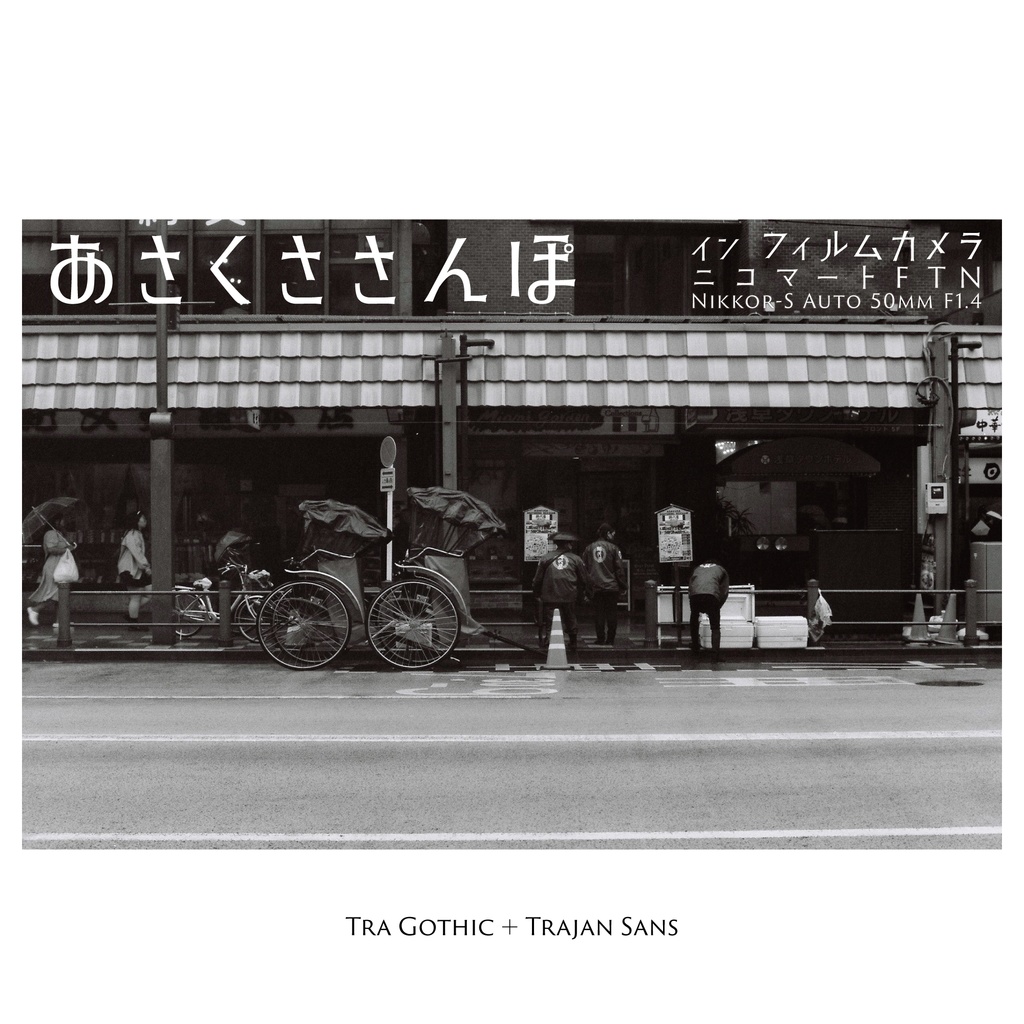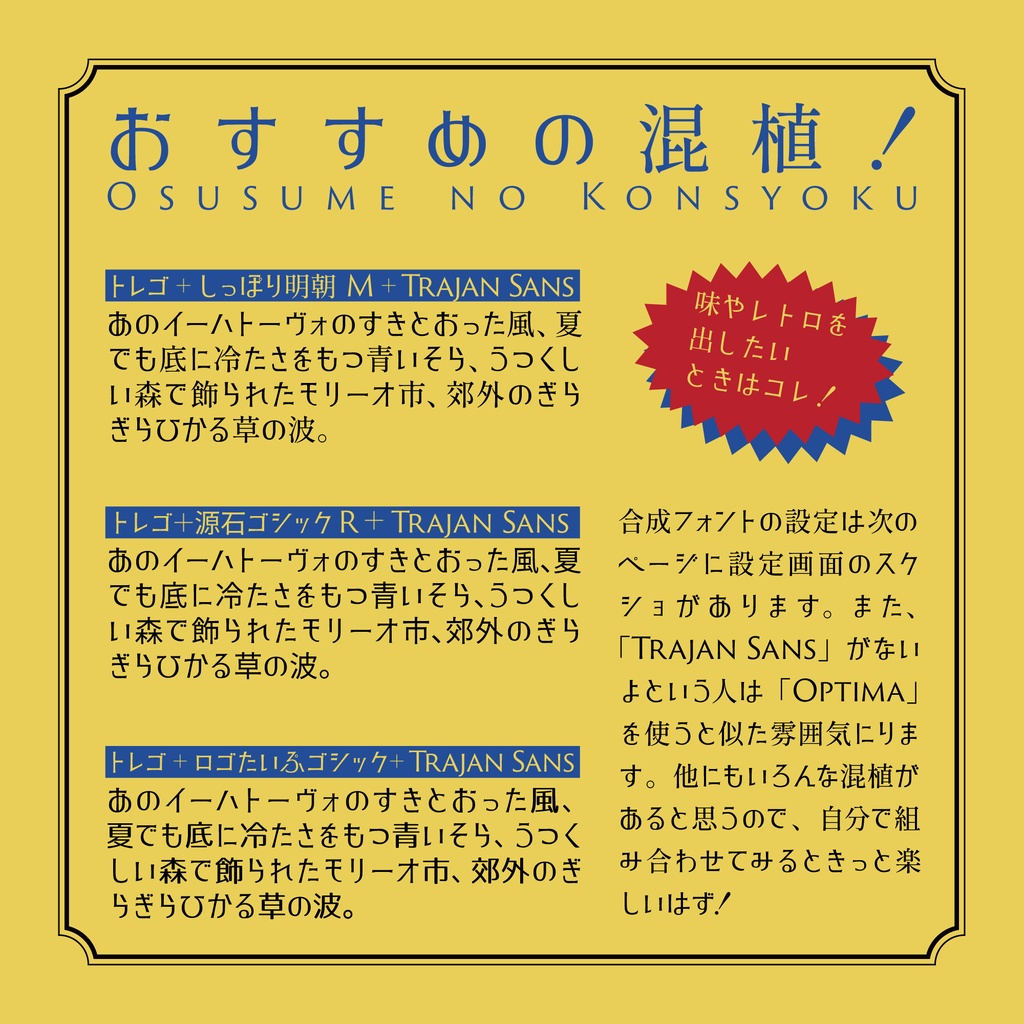
【フリーフォント】「トレゴ」昭和レトロな雰囲気
この度はフリーフォント「トレゴ」をダウンロードいただき誠にありがとうございます。 ■書体概要 欧文書体「Trajan Sans」から着想を得て作られたフォントです。 なんと、古い商店街の美容室や婦人服やの看板のようなレトロさを持ち合わせたものに仕上がっています。 また、混植を想定した作りになっています。boothの紹介画像にあるような混植を行うと漢字も使えますのでぜひ ■収録字形 ひらがな、カタカナ ■ご利用にあたり 商用・個人利用可能です。また、著作権は放棄しておりません。 個人的なフォントの改変は自由ですが、派生フォントの配布はお控えください。 フォントファイル単体の二次配布は禁止です。 このフォントを使用したことによるトラブルや損害に関しては一切の責任を持ちません。 ■ご不明な点がありましたら Twitter(@iose_sakana)のDMまでご連絡お願いします。 2023/08/28 Ver1.000 公開 Copyright (c) 2023 Typographish All Rights Reserved.